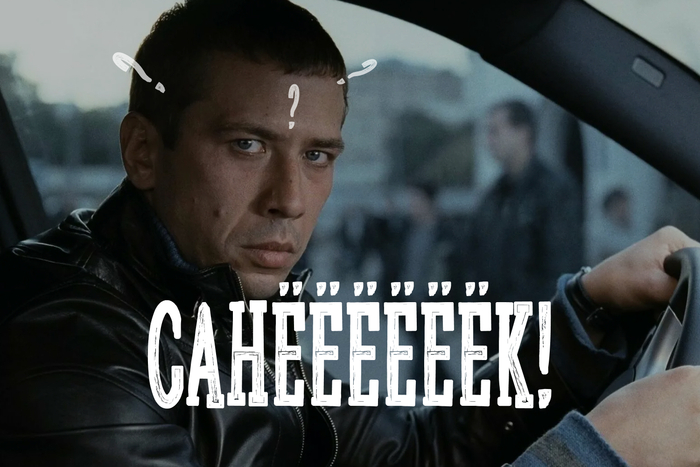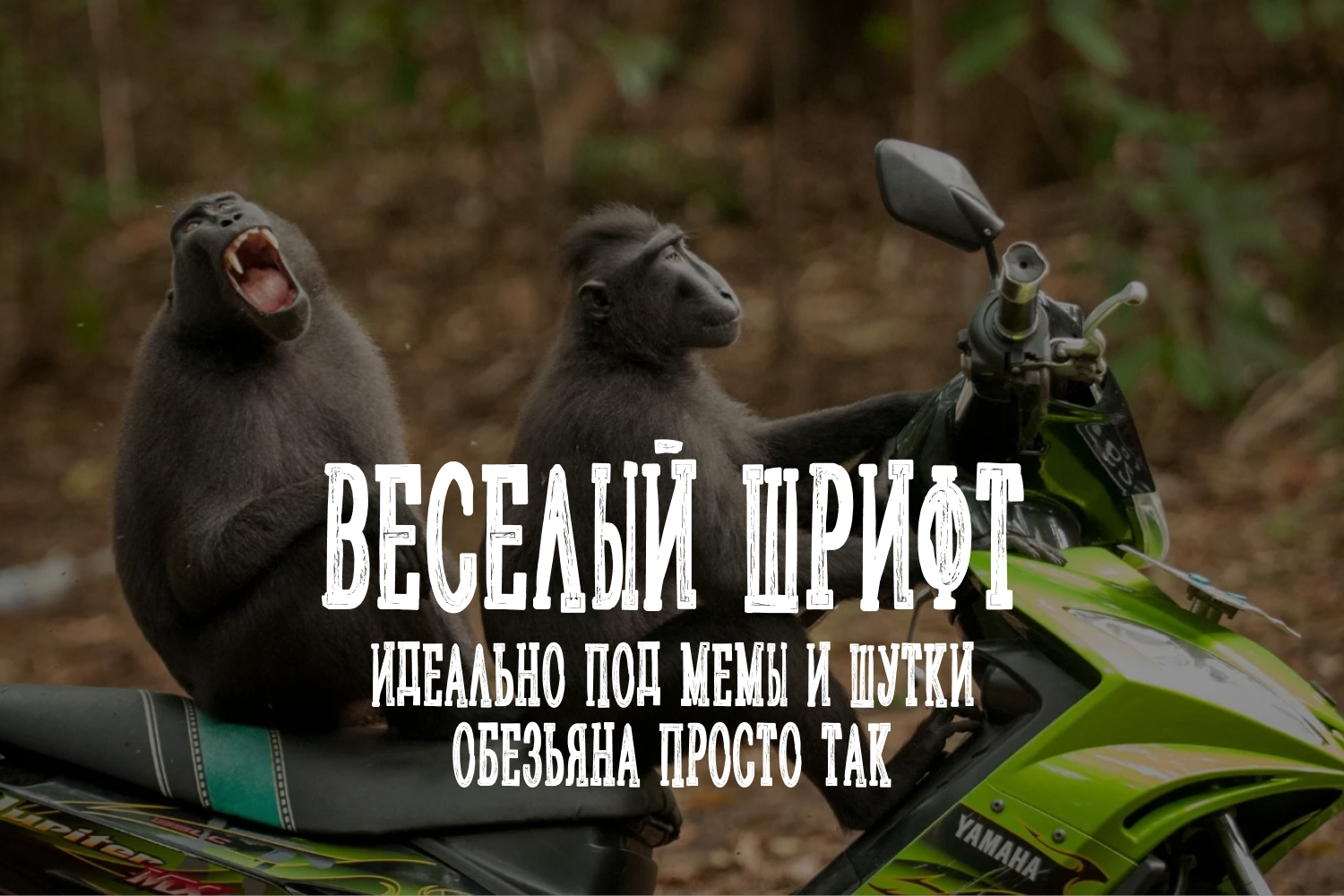
Шрифт "Санёк"
Саня ты в порядке? Ты в порядке? Саня!!! Васек уже был. Настал час Сани. Кириллизация шрифта от Iordanis Passas. Веселый шрифт. Отлично подойдет под юмористический дизайн, под кофейню и под какой-нибудь барбер.
Автор кириллизации: Денис Кукушкин